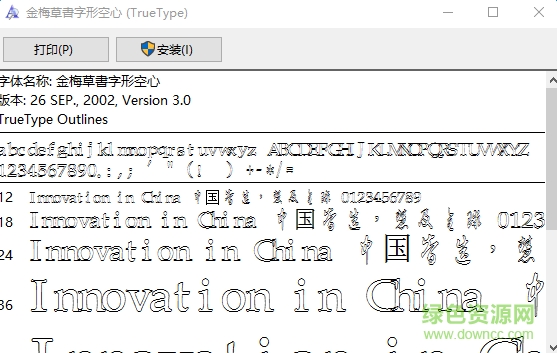
金梅草書(shū)字形空心字體是金梅字庫(kù)中的一款空心字體,這樣的字體比較有特色,寫(xiě)出來(lái)的字也是很好看的,用于藝術(shù)設(shè)計(jì)、廣告設(shè)計(jì)都是很不錯(cuò)的,歡迎有需要的朋友來(lái)綠色資源網(wǎng)下載。
金梅草書(shū)字形空心字體這款字體筆形非常的俊美,而且比較活潑,不像普通的字體那樣呆板,有一種很端莊、大方的感覺(jué),非常的好用,大家也可以來(lái)綠色資源網(wǎng)下載試試。